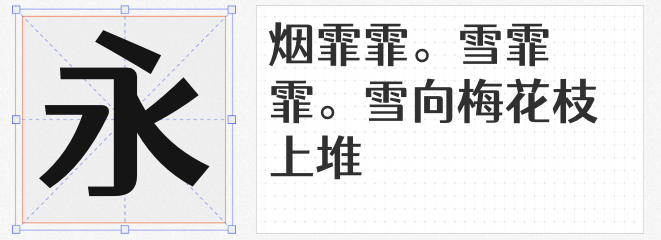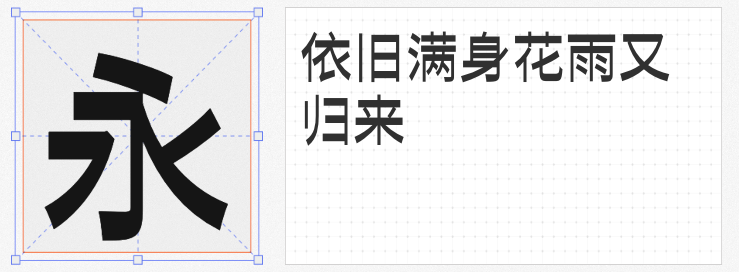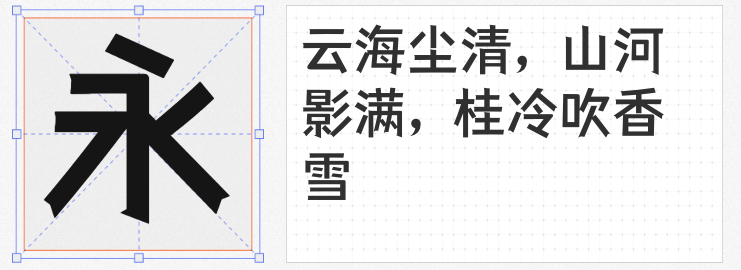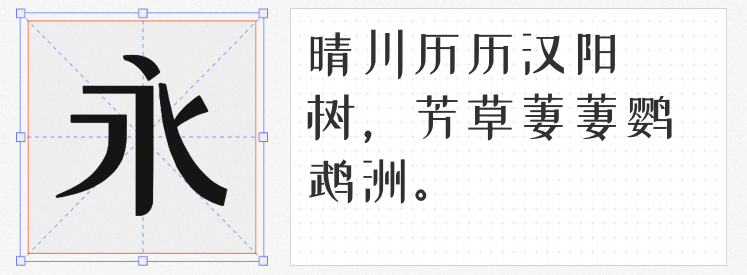
在海报设计的视觉语言中,字体是传递情绪、塑造风格的核心元素。本文精选四款兼具艺术性与实用性的免费商用字体,从创新几何到人文温度,为设计师提供多元的创意工具。
这款字体以「剑身」为灵感,将6763个汉字的笔画简化为修长锐利的几何形态。捺笔末端切断处理形成整齐的几何切面,转折处硬朗如刀锋,却在笔画交界处巧妙露出「小脚」打破机械感。在设计海报中使用,其锋芒毕露的笔画与极简布局形成强烈视觉张力,而修长的字面比又赋予标题呼吸感。
这款字体,将篆刻的「刀痕」转化为笔形特征:竖画模拟刀刻的锐利沟槽,横折处却以圆角过渡,形成「内方外圆」的独特张力。在运动品牌海报中,粗字重的「与墨」可突出力量感,而配套的英文标点沿用相同设计语言,确保中英混排的视觉统一。其GB2312字符集覆盖6763个汉字,满足商业项目的完整需求。
基于思源黑体改造的这款字体,通过「逆反差」设计颠覆传统认知:横画纤细如发丝,竖画粗壮似钢柱,形成强烈的视觉对比。在音乐节海报中,这种矛盾美学恰好呼应了摇滚乐的冲突与释放,而基于思源黑体的结构基础又保证了小字号下的可读性。其30892字符集支持多语言排版,成为国际化项目的理想选择。
作为站酷首款公益家族字体,渔阳体将宋体的典雅与黑体的现代感熔铸一炉:横画末端保留宋体三角饰角,竖画却采用黑体的无衬线设计,转折处的圆角处理则赋予字体人文温度。